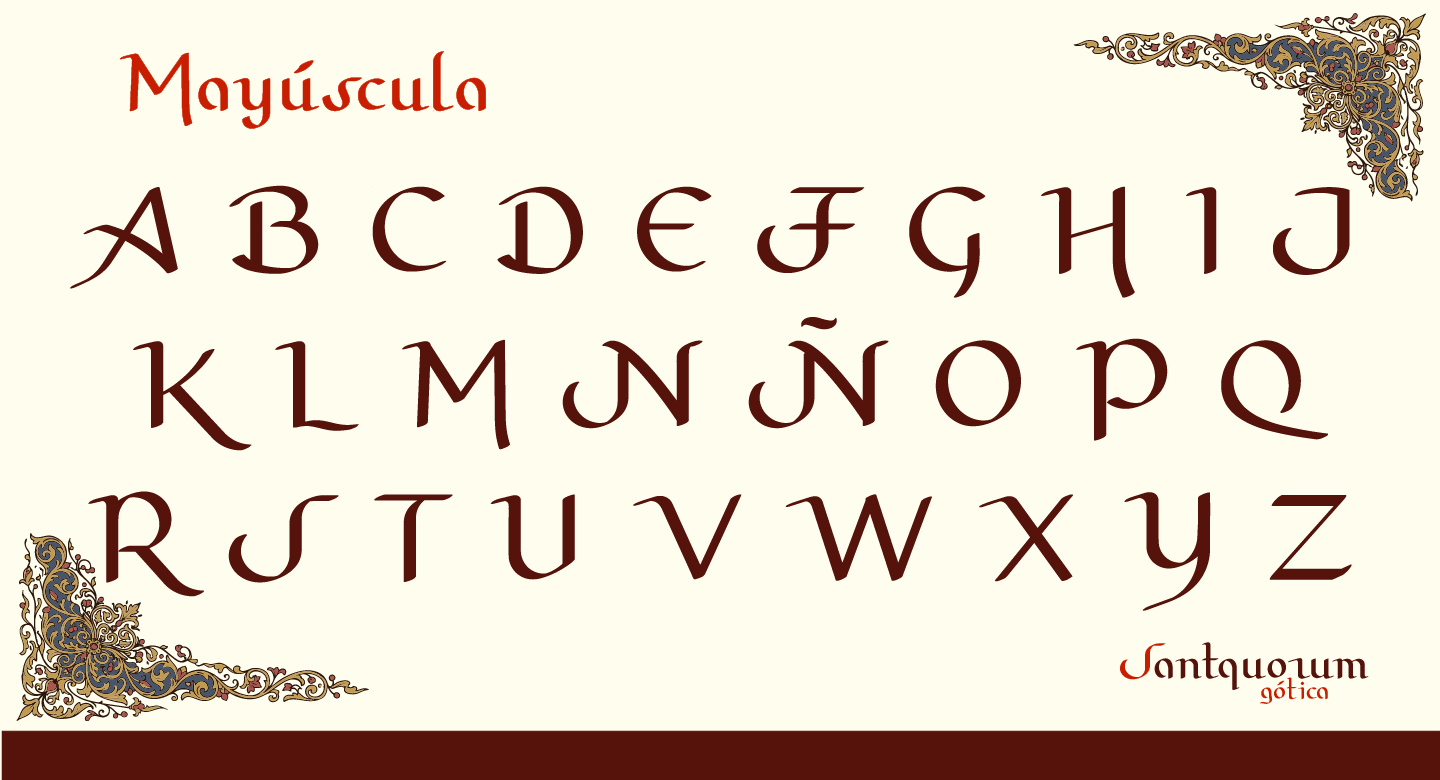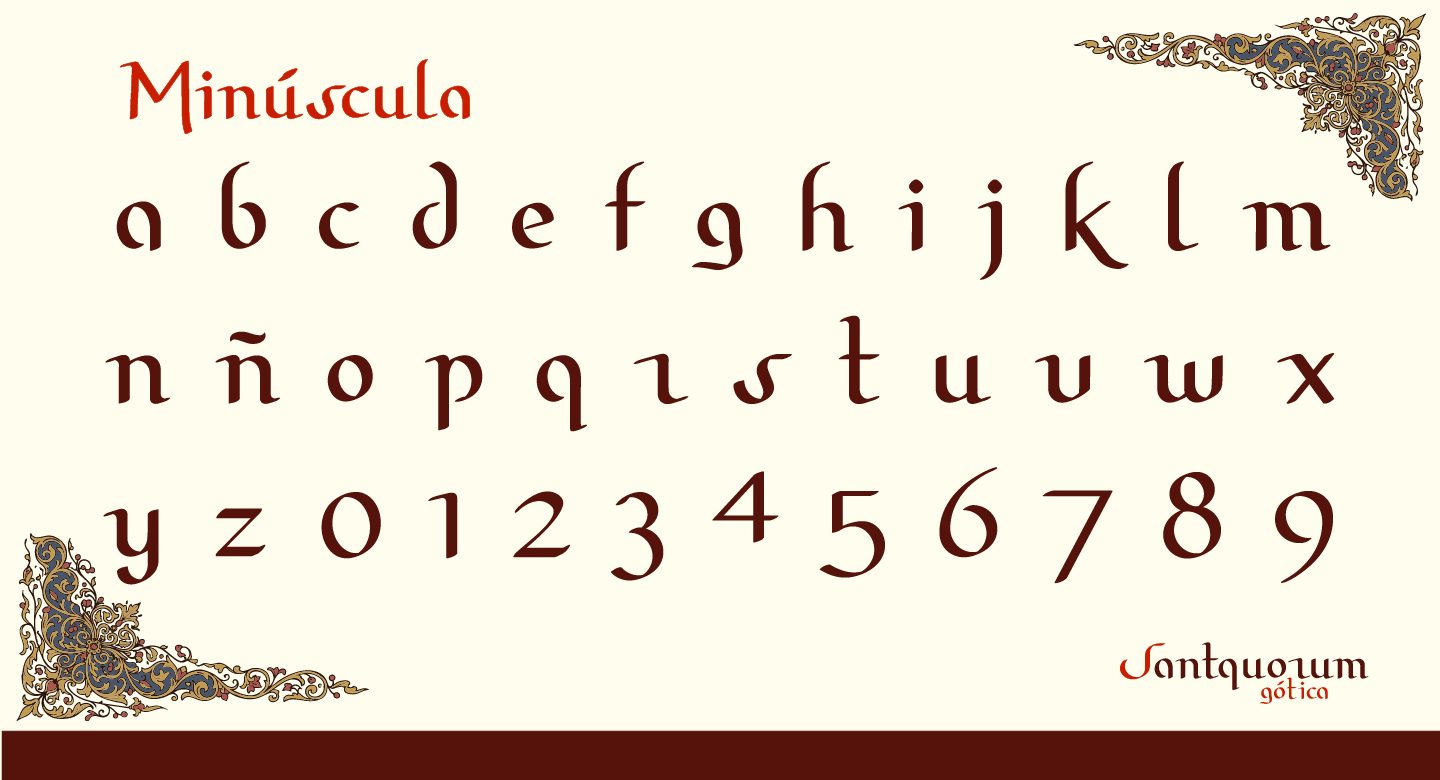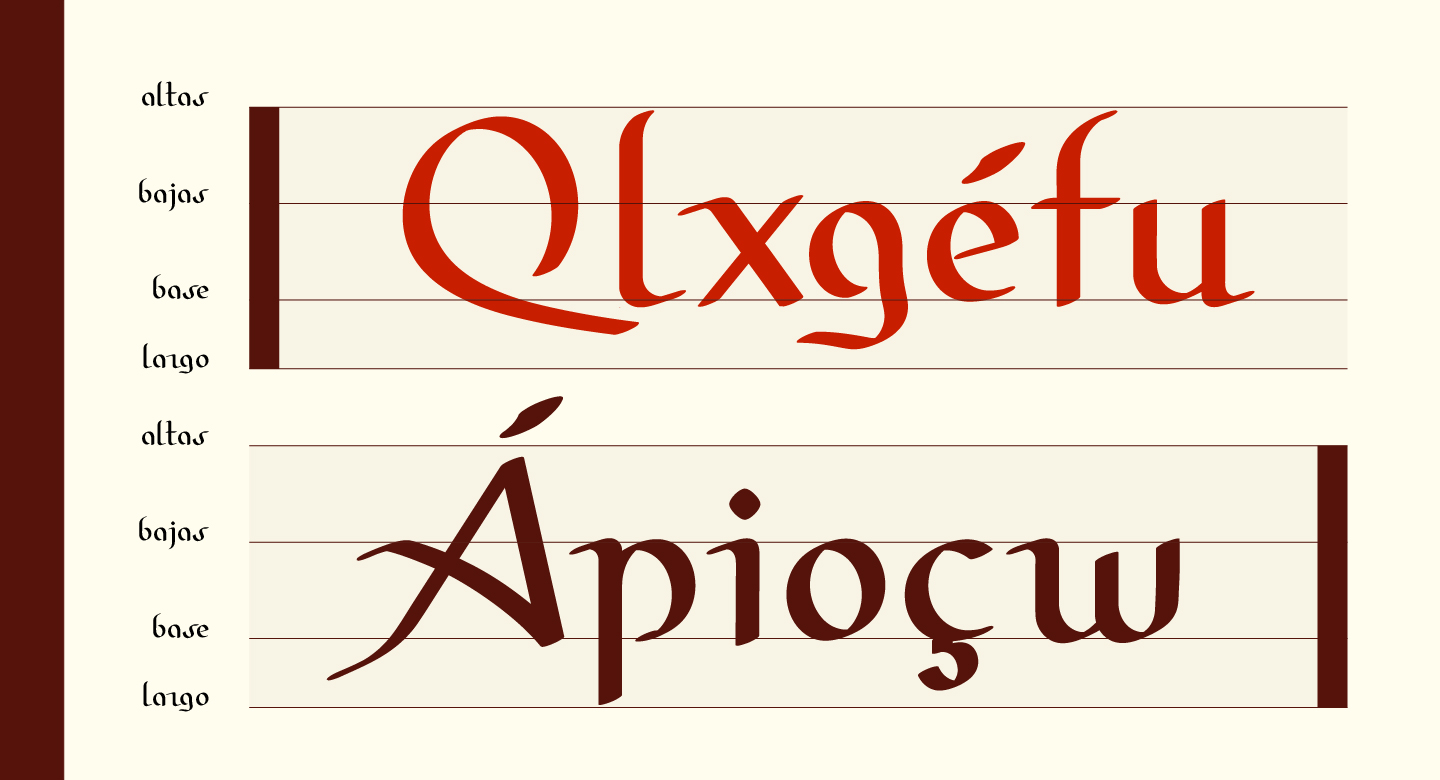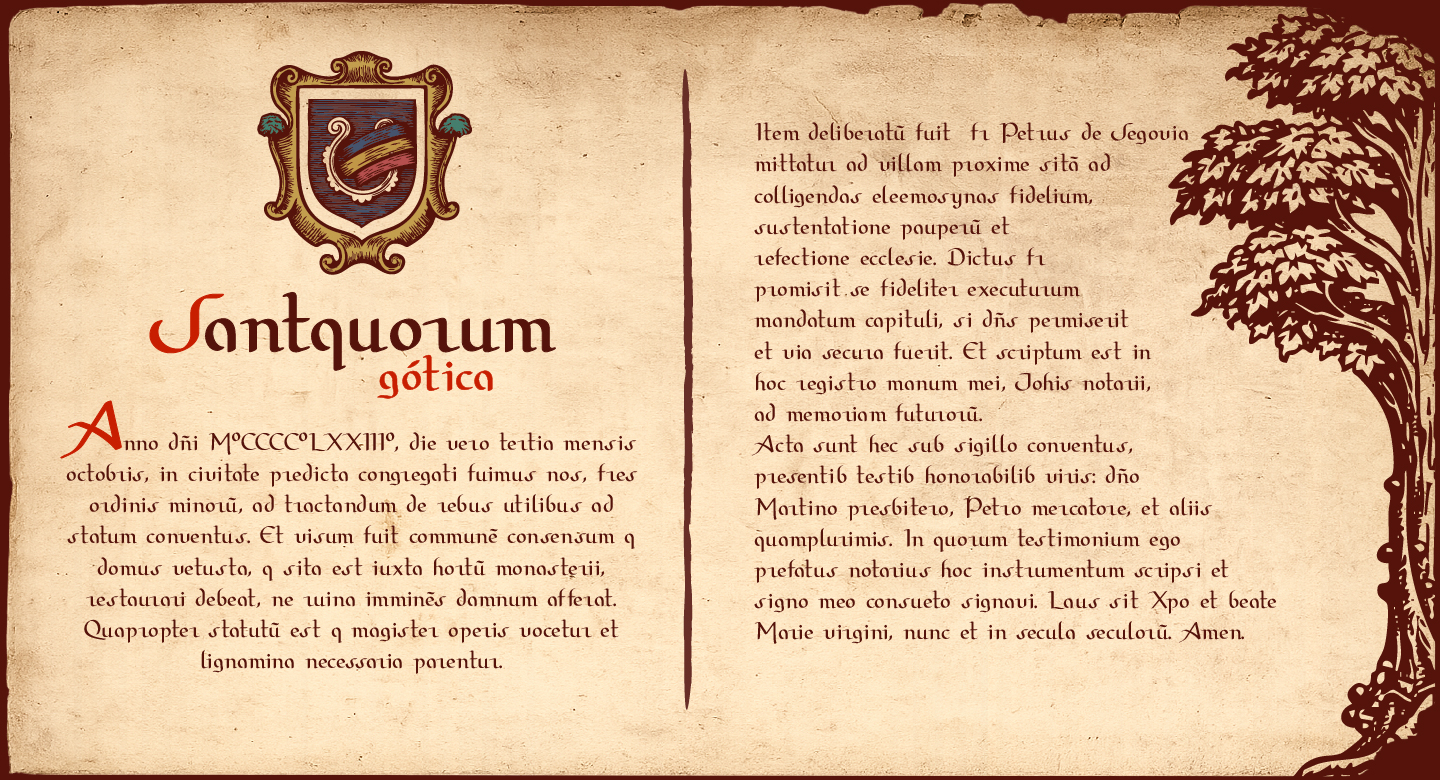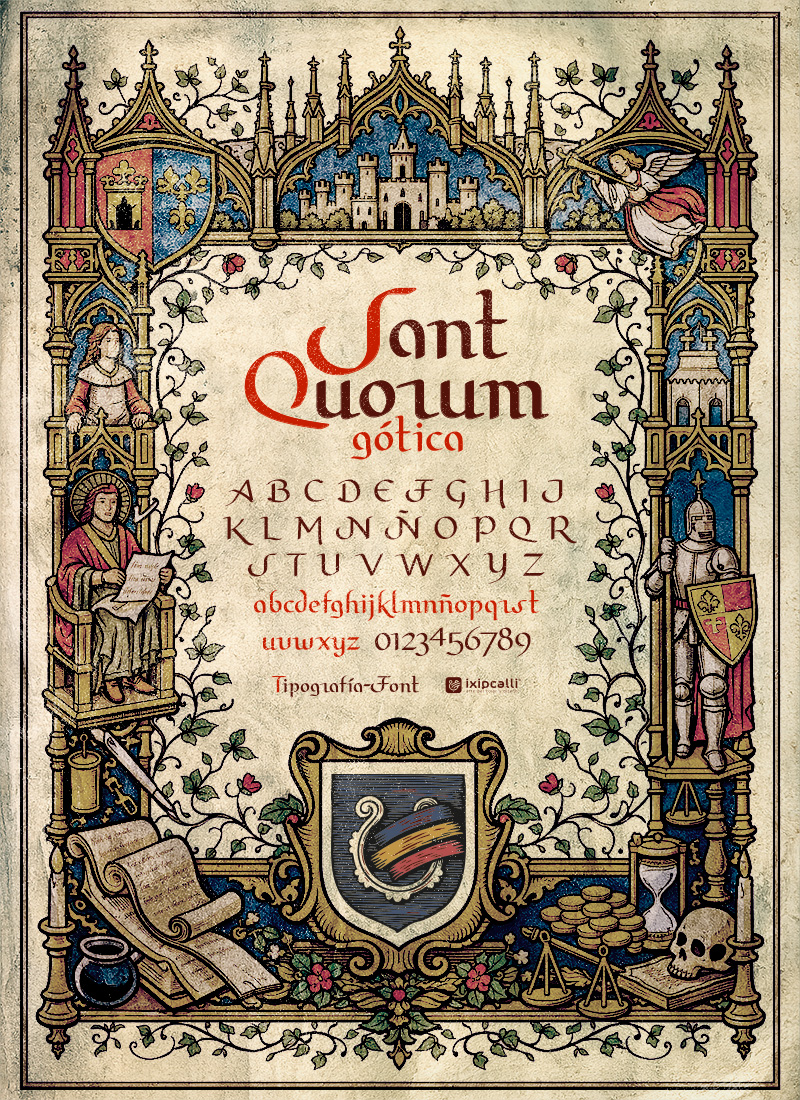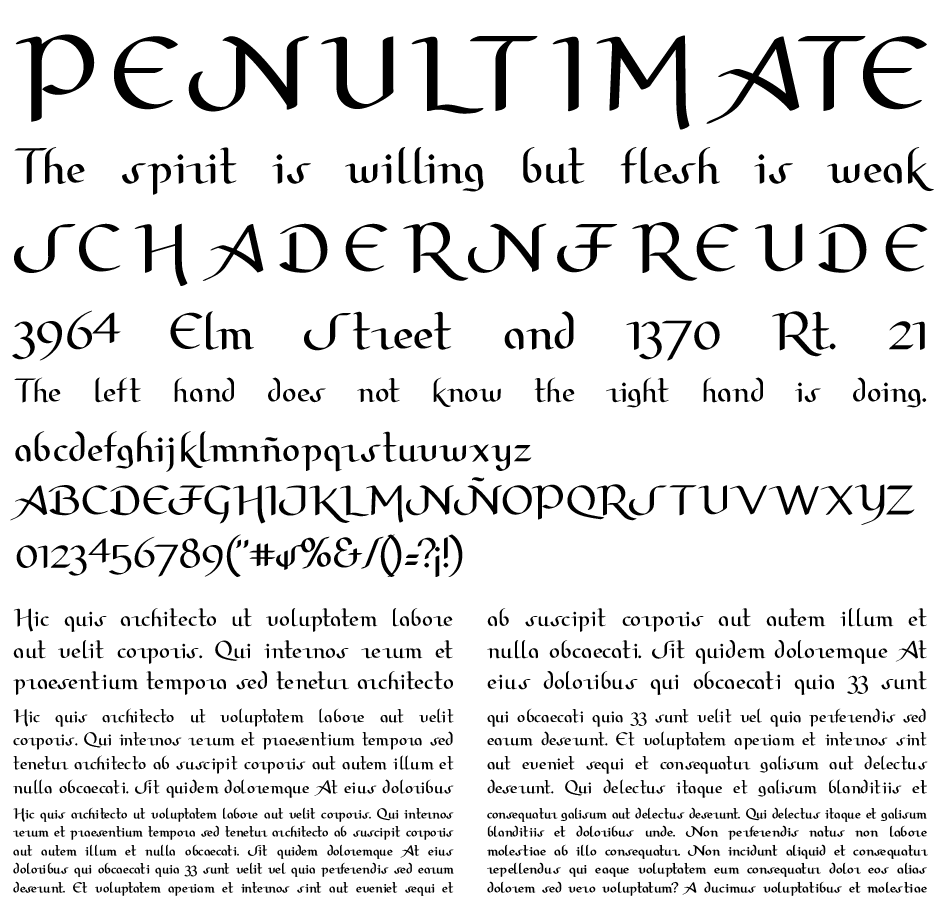
santquorum gotica
Descripción
(2025) - Santquorum Gótica es una tipografía de estilo gótico medieval, inspirada en documentos históricos de los siglos XIV al XVI. Su nombre significa “Santa Asamblea”, pertenenciente a la familia tipográfica del mismo nombre compuesta por cuatro evoluciones estilísticas que recorren un desarrollo conceptual, desde una forma antigua hasta una versión sans serif contemporánea. Esta variante de estilo gótico refuerza autenticidad histórica. Su construcción formal está pensada para evocar la estética de los textos medievales góticos sin sacrificar claridad visual.
Es especialmente adecuada para proyectos que buscan recrear la apariencia de documentos históricos, ediciones facsimilares, publicaciones académicas o identidades visuales con una fuerte referencia patrimonial. La estructura de sus trazos favorece una lectura fluida, permitiendo que la tipografía funcione también dentro de composiciones editoriales contemporáneas con un carácter neoclásico.